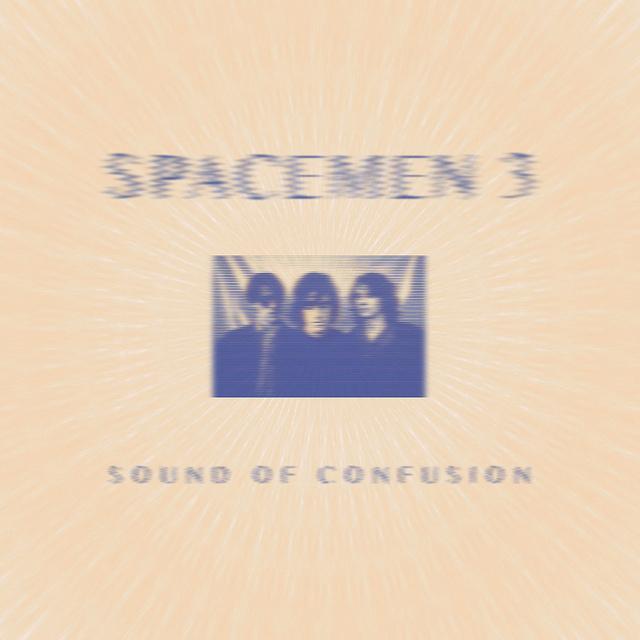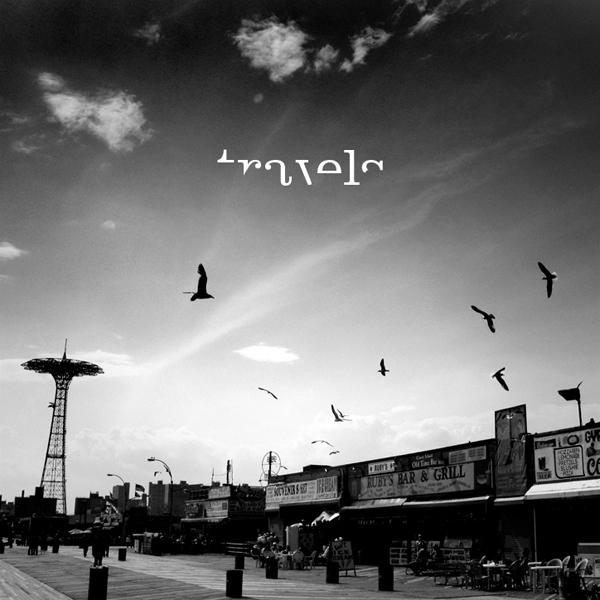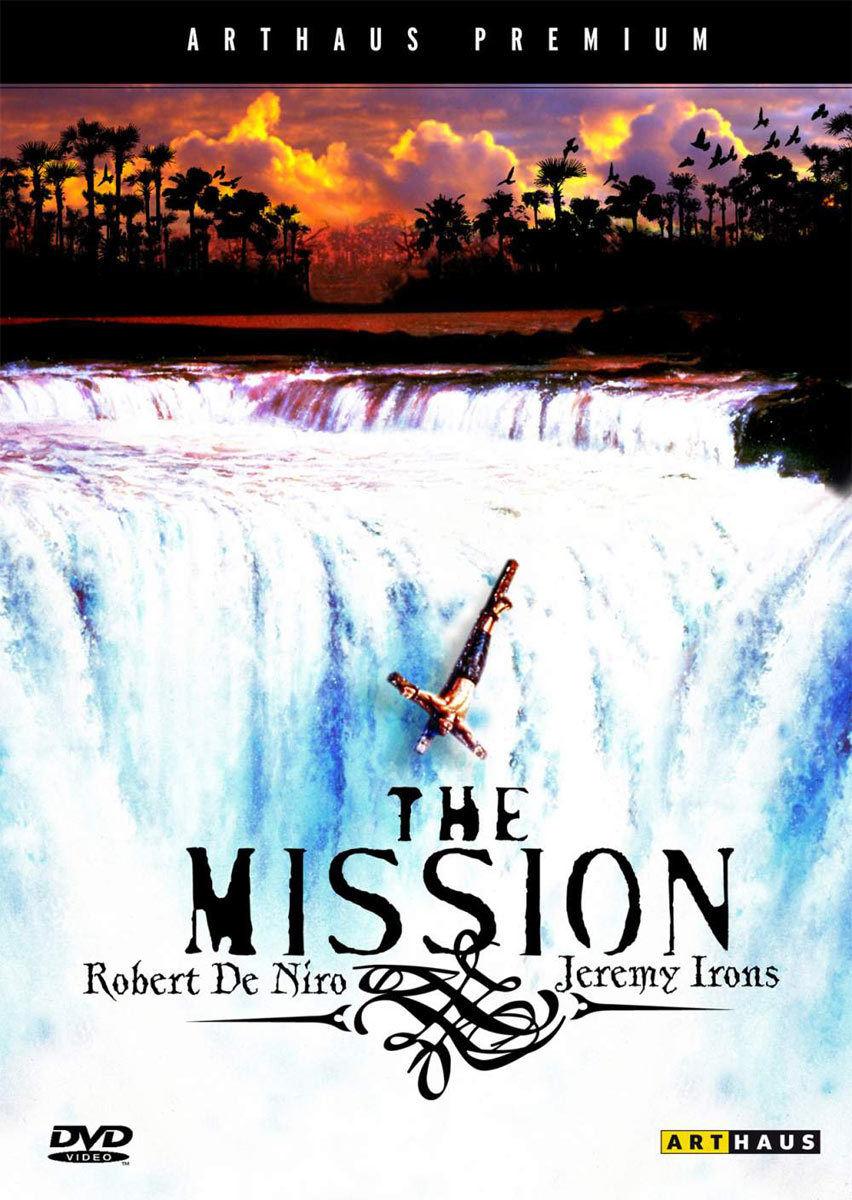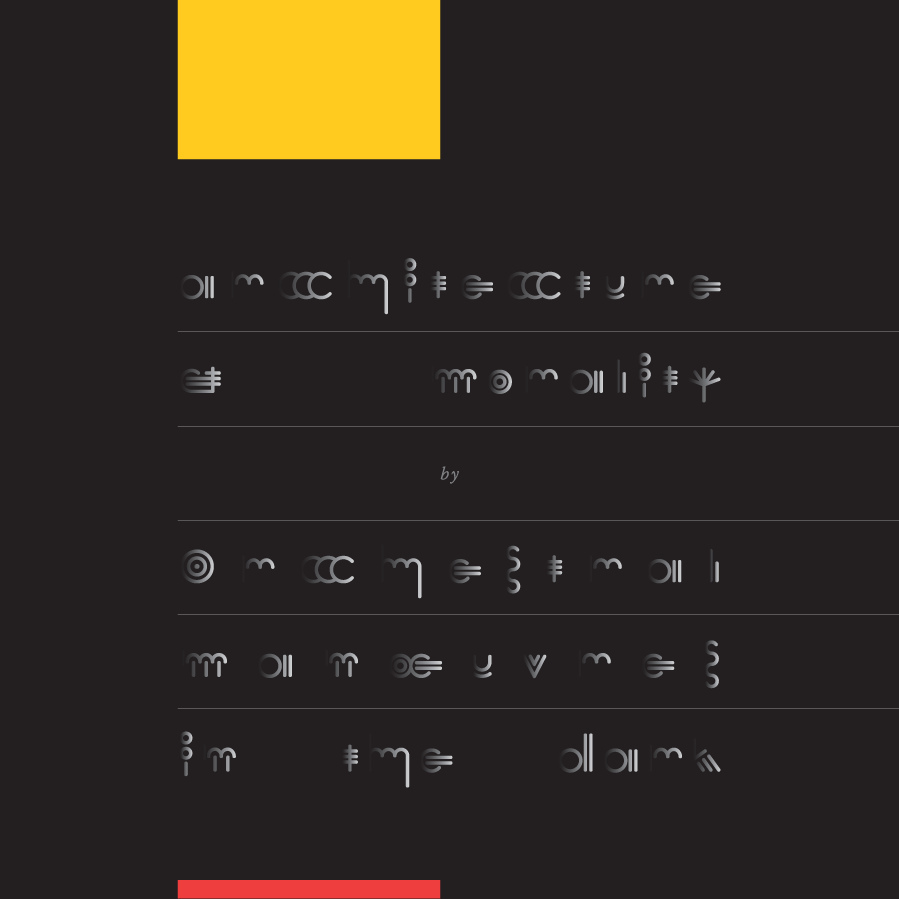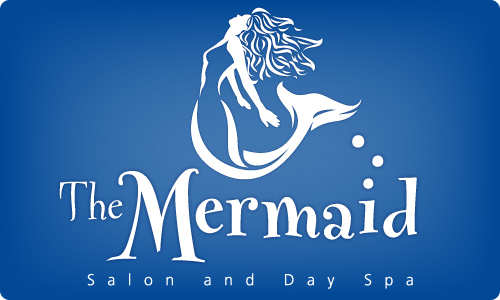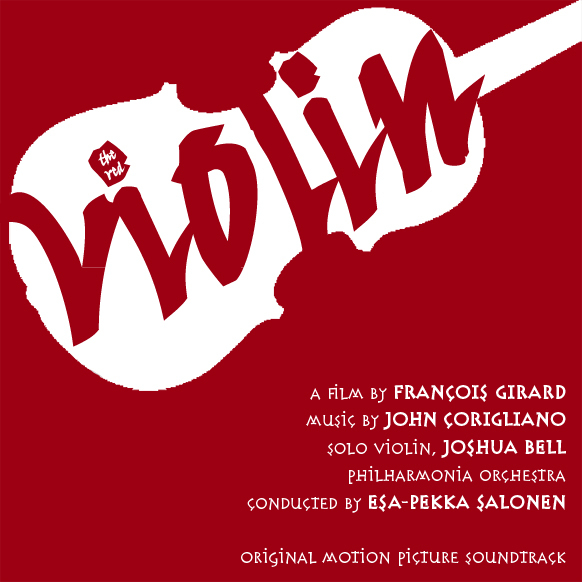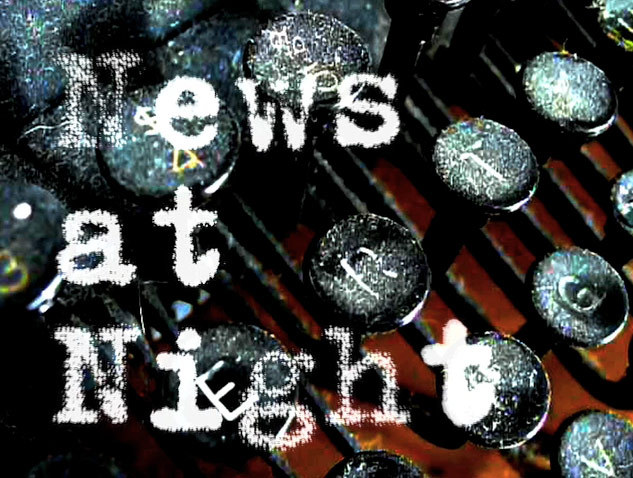
Frage: Geheimnisvoll, Lebhaft und Auffallend
Egal welche Klassifizierung oder Grotesk, Antiqua, Script, …?
Beziehungsweise für welchen Zweck willst Du die Schrift einsetzen? Überschriften, Fließtext, Logo, …?
Zu viel Schätzing gelesen, wa?
… Unicase-Antiqua-Schriften.
Wobei die kein Ausbund an Lebhaftigkeit sind. :-)
Nicht unbedingt, aber das kommt ja auch wieder auf die restliche Gestaltung an.
Ach Du meinst »Schätzing«!
Stimmt. Und die Informationen könnten ruhig noch etwas Vertiefung vertragen. Bei »Geheimnisvoll, Lebhaft und Auffallend« lässt sich immer noch in viele Richtungen denken.
Bei »Geheimnisvoll, Lebhaft und Auffallend« lässt sich immer noch in viele Richtungen denken.
Zum Beispiel:
FF Fontesque by Nick Shinn
FF Fancy Writing by Timothy Donaldson, FF Chelsea by Frank Heine
FF Merlin by Nick Shinn
FF Trixie HD by Erik van Blokland
FF You Can Read Me by Phil Baines
FF Yokkmokk by Elke Herrnberger
FF Nelio Square Bar Script by Sami Kortemäki
FF Singer Sans by Matthias Thiesen
Klar, jede betont einen bestimmten Aspekt mehr einen anderen weniger. Und wie Schnitzel schon sagte, die Gesamtgestaltung steigert oder aber mindert die Wirkung. Wäre beispielsweise bei Arielle das Blau nicht so leuchtend sondern dunkler und die Schriftfarbe anders gewählt, wirkte die Fontesque sicher geheimnisvoller, etc. Außerdem kann man – denke ich zumindest – schön erkennen, dass man »lebhaft« nicht nur unbedingt mit Kursivstellung erreicht. Auch Struktur, bestimmte Formenkombinationen, usw. können Schrift beleben.
Wie Du siehst, es gibt viele Möglichkeiten. Eingrenzen kannst nur Du sie. :-)